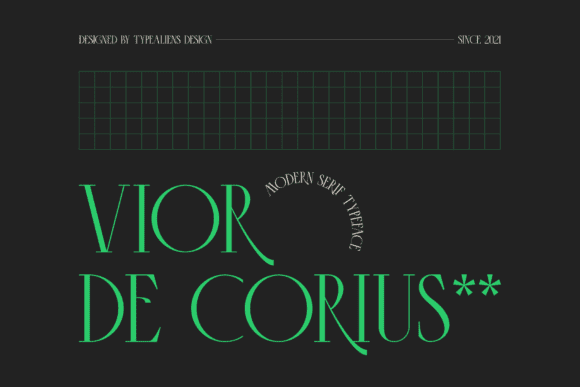
Название: Vior de Corius Font (2021)
Vior De Corius - тонкий, высокий шрифт с четкими засечками.
Он идеально подходит для модного брендинга или редакционного дизайна.